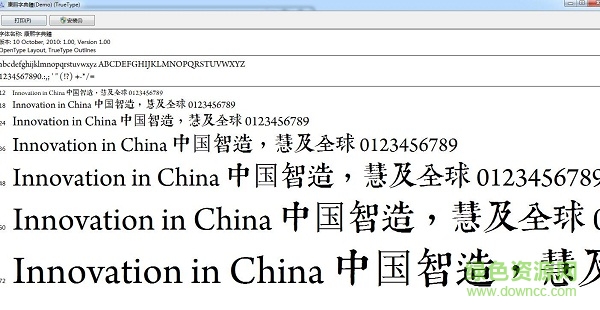
tpldkhangxidictdemo是什么字體?tpldkhangxidictdemo字體又叫康熙字典體(demo)字體,該字體強調傳承感,用筆收斂,字形端正,沒有過多的修飾,需要的朋友歡迎免費下載!
1.《康熙字典》是張玉書、陳廷敬等三十多位著名學者奉康熙圣旨編撰的一部具有深遠影響的漢字辭書。
2.《康熙字典》吸收了歷代字書編纂的有益經驗,又集中了傳統字書編纂中規(guī)模最大的30人編寫隊伍,加上是御敕纂修,問世后影響巨大。
3.《康熙字典》收字多,字之別體、俗寫均錄,其文字音義書證廣為引用,其體例成為后出字書的藍本。